34 ฟอนต์สยองขวัญที่ดีที่สุด 2023 (ฟรีและพรีเมียม)
เผยแพร่แล้ว: 2023-08-06คุณเป็นนักออกแบบกราฟิกที่กำลังมองหาฟอนต์ที่สมบูรณ์แบบเพื่อเพิ่มความสยองขวัญให้กับโปรเจ็กต์ของคุณหรือไม่? มองไม่เพิ่มเติม! ในบล็อกโพสต์นี้ เราได้รวบรวมรายชื่อฟอนต์สยองขวัญที่ดีที่สุด 34 แบบที่จะช่วยเพิ่มระดับการออกแบบเกมของคุณได้อย่างแน่นอน
แต่ก่อนที่เราจะดำดิ่งสู่โลกอันน่าตื่นเต้นของฟอนต์ชวนสยอง คุณอาจสงสัยว่า “ทำไมฉันต้องใช้ฟอนต์สยองขวัญสำหรับงานออกแบบของฉัน” คำตอบนั้นง่าย ฟอนต์มีบทบาทสำคัญในการกำหนดความสวยงามโดยรวมของงานออกแบบ และการใช้ฟอนต์ที่เหมาะสมสามารถสร้างบรรยากาศที่น่าดึงดูดใจและเยือกเย็นได้
คุณคาดหวังอะไรจากบทความนี้ เราได้ทำการวิจัยเพื่อคุณและรวบรวมคอลเลกชันแบบอักษรสยองขวัญ 34 อันดับแรกที่จะทำให้คุณสั่นสะท้าน
ไม่ว่าคุณจะกำลังทำโปรโมชันฮาโลวีน โปสเตอร์หนังสยองขวัญ หรือปกหนังสือสบายๆ ฟอนต์เหล่านี้จะเพิ่มสัมผัสแห่งความมืดและความน่าสยดสยองให้กับงานออกแบบของคุณ ตั้งแต่ฟอนต์แบบกอธิคที่หรูหราไปจนถึงสไตล์ลายมือที่น่าขนลุก เรารวบรวมไว้หมดแล้ว
ตอนนี้ มาดูรายชื่อฟอนต์สยองขวัญที่ดีที่สุดของเรากัน ในบทความนี้ เราจะสำรวจตัวเลือกต่างๆ มากมาย รวมถึงฟอนต์ที่ได้รับแรงบันดาลใจจากภาพยนตร์สยองขวัญคลาสสิก สไตล์วินเทจ และรูปแบบที่ทันสมัย
แบบอักษรแต่ละแบบมาพร้อมกับคำอธิบายสั้น ๆ และลิงก์สำหรับดาวน์โหลด ทำให้คุณสามารถค้นหาและนำแบบอักษรที่เหมาะสมไปใช้ในโครงการของคุณได้ง่าย คาดเข็มขัดนิรภัยและเตรียมพร้อมที่จะค้นพบแบบอักษรที่ชวนเสียวสันหลังที่สมบูรณ์แบบ ซึ่งจะช่วยยกระดับการออกแบบของคุณไปอีกขั้น
แบบอักษรสยองขวัญระดับพรีเมียมที่ดีที่สุด
กำลังมองหาที่จะเพิ่มความสยองขวัญให้กับโครงการออกแบบของคุณหรือไม่? ไม่ต้องมองหาที่ไหนไกลไปกว่าคอลเลกชันแบบอักษรพรีเมียมที่ดีที่สุดที่เราคัดสรรมา
ฟอนต์ที่คัดสรรมาอย่างดีเหล่านี้รับประกันได้ว่าจะยกระดับงานออกแบบของคุณและทำให้พวกมันดูสวยงามจนน่าตกใจ ตรวจสอบตัวเลือกอันดับต้น ๆ ของเราด้านล่างและเตรียมพร้อมที่จะปลดปล่อยความคิดสร้างสรรค์ของคุณ!
แบบอักษรสยองขวัญ
Horror Typeface เป็นฟอนต์สำหรับแสดงผลที่โดดเด่นซึ่งเพิ่มความสยองขวัญให้กับงานออกแบบของคุณ ทำให้เป็นตัวเลือกที่สมบูรณ์แบบสำหรับการถ่ายทอดข้อความของคุณอย่างมีประสิทธิภาพ ไม่ว่าคุณกำลังสร้างโปสเตอร์ภาพยนตร์ โลโก้ ออกแบบเสื้อผ้า หรือปกอัลบั้ม ฟอนต์นี้จะสร้างผลกระทบอย่างแน่นอน
ด้วยบรรยากาศที่น่าขนลุกและน่ากลัว มันสร้างโทนเสียงที่เหมาะสมสำหรับโปรเจกต์แนวสยองขวัญ
แบบอักษรนี้ออกแบบมาโดยเฉพาะสำหรับผู้ที่ชื่นชอบสยองขวัญ นักออกแบบกราฟิกที่ต้องการยกระดับโปรเจ็กต์ของตนไปอีกขั้น
สไตล์ที่เป็นเอกลักษณ์และแตกต่างของมันจับใจความสำคัญของความสยองขวัญ ทำให้เหมาะสำหรับการสร้างฉากและชื่อภาพยนตร์ที่น่าหลงใหล ความสามารถรอบด้านทำให้สามารถใช้กับสื่อต่างๆ ได้ตั้งแต่โปสเตอร์ไปจนถึงใบปลิวขนาดใหญ่ สร้างงานออกแบบที่เหนียวแน่นและสวยงาม
ดาร์กสไตน์
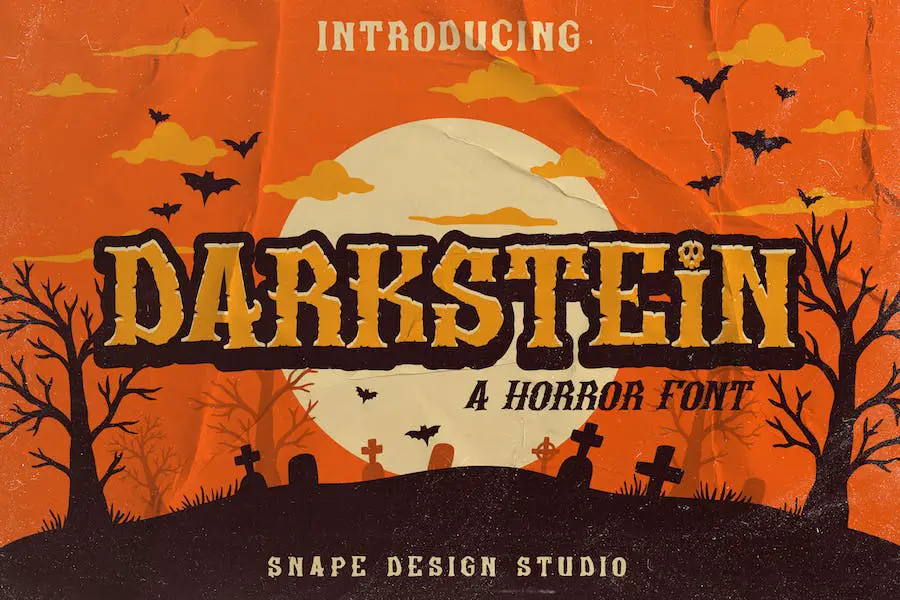
Darkstein เป็นฟอนต์สยองขวัญที่เหมาะเป็นอย่างยิ่งสำหรับการเพิ่มสัมผัสที่น่ากลัวให้กับงานออกแบบของคุณ ไม่ว่าคุณจะกำลังทำโปสเตอร์ปาร์ตี้ฮัลโลวีนหรือสร้างโลโก้ภาพยนตร์ที่น่ากลัว Darkstein จะทำให้โปรเจกต์ของคุณโดดเด่นอย่างแน่นอน
ฟอนต์นี้ดูขี้เล่นแต่น่ากลัว ทำให้ใช้งานได้หลากหลายสำหรับโปรเจ็กต์ต่างๆ เช่น สารคดี ชื่อภาพยนตร์ ปกหนังสือ และอื่นๆ
ให้ Darkstein ปลดปล่อยเสน่ห์ที่น่าขนลุกและนำความรู้สึกหนาวเหน็บมาสู่งานออกแบบของคุณ ไม่ว่าคุณจะสร้างโปรเจ็กต์ฮัลโลวีนที่น่าขนลุกหรือเพียงแค่ต้องการเพิ่มสัมผัสแห่งความมืดให้กับงานของคุณ Darkstein คือตัวเลือกที่สมบูรณ์แบบ
เตรียมพร้อมที่จะทำให้งานออกแบบของคุณโดดเด่นด้วยฟอนต์ชวนขนหัวลุกนี้
ความสุขสยองขวัญ
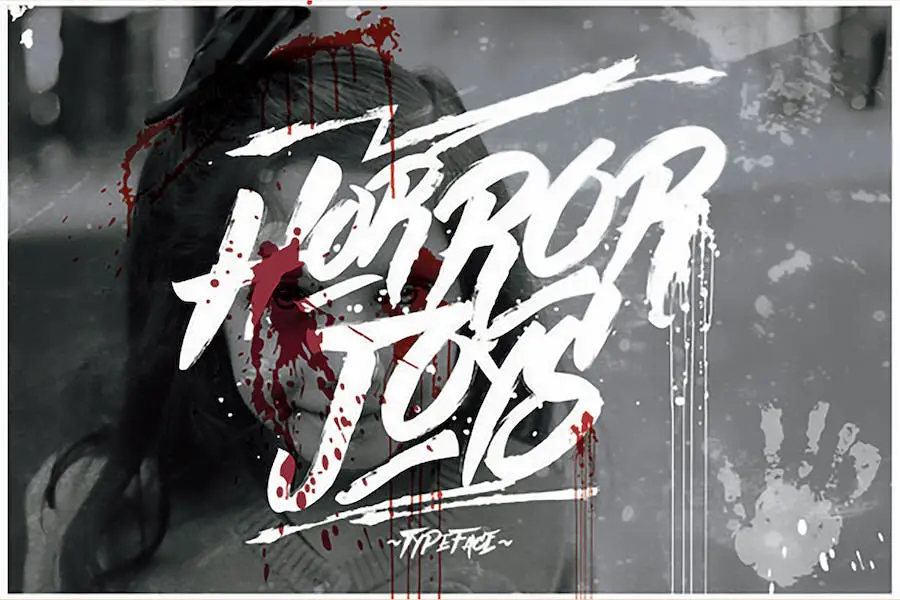
Horror Joys เป็นแบบอักษรสยองขวัญที่ได้รับแรงบันดาลใจจากภาพยนตร์สยองขวัญ มันให้ความรู้สึกแบบแฮนด์เมดที่เพิ่มความน่าขนลุกให้กับงานออกแบบที่เกี่ยวกับหนังสยองขวัญ โปสเตอร์หนัง โปสเตอร์เพลงดังๆ และโปรเจกต์ที่คล้ายกัน
หากคุณชอบความลึกลับ ตำนาน และเรื่องผี ฟอนต์นี้เหมาะสำหรับคุณ เตรียมพร้อมเพิ่มความหลอนให้กับงานออกแบบของคุณด้วย Horror Joys
ด้วยการออกแบบที่ได้รับแรงบันดาลใจจากภาพยนตร์สยองขวัญ Horror Joys นำบรรยากาศที่ไม่เหมือนใครและหนาวเหน็บมาสู่โปรเจ็กต์ของคุณ ความสวยงามแบบแฮนด์เมดทำให้แตกต่างจากฟอนต์อื่นๆ ทำให้งานออกแบบของคุณรู้สึกแตกต่างและน่าขนลุก
ไม่ว่าคุณจะกำลังสร้างโปสเตอร์ภาพยนตร์ หน้าปกเพลย์ลิสต์ชวนสยอง หรืองานออกแบบใดๆ ที่ต้องการสัมผัสที่น่าขนลุก Horror Joys จะยกระดับงานของคุณไปสู่ระดับใหม่ทั้งหมด
ซูซานสไตน์
Suzanstein เป็นแบบอักษรที่ผสมผสานองค์ประกอบสยองขวัญและเรโทรเพื่อสร้างการออกแบบที่หรูหราและซับซ้อนยิ่งขึ้น มันนอกเหนือไปจากธีมผีและเศร้าทั่วไปที่เกี่ยวข้องกับความมืด ช่วยให้คุณสำรวจความเป็นไปได้ที่หลากหลายยิ่งขึ้น
ฟอนต์นี้ไม่จำกัดเฉพาะธีมสยองขวัญเท่านั้น นอกจากนี้ยังสามารถใช้สื่อถึงความมืดมน ความหลงใหล ความอ่อนเยาว์ ความเพ้อฝัน และแม้แต่ประเด็นทางสังคม มีความสามารถรอบด้านและสามารถนำสัมผัสที่ไม่เหมือนใครมาสู่งานออกแบบของคุณได้
Suzanstein เป็นฟอนต์ตัวพิมพ์ใหญ่ทั้งหมดที่มีตัวพิมพ์เล็ก นอกจากนี้ยังมีคุณสมบัติ OpenType ซึ่งเพิ่มความหลากหลายและตัวเลือกที่สร้างสรรค์ให้กับงานออกแบบของคุณ ไม่ว่าคุณจะออกแบบโลโก้ โปสเตอร์ ใบปลิว คำคม ปกหนังสือ หรือบทความสั้นๆ Suzanstein คือตัวเลือกที่ยอดเยี่ยม
ความเศร้าโศก
Sorrow – ฟอนต์สยองขวัญเป็นฟอนต์สำหรับตกแต่งที่นำกลิ่นอายน่ากลัว น่าขนลุก และลึกลับมาสู่โปรเจ็กต์การออกแบบใดๆ เหมาะอย่างยิ่งสำหรับผลิตภัณฑ์ที่จับต้องได้และดิจิทัลที่มีธีมสยองขวัญ น่ากลัว หรือโกธิค แบบอักษรนี้จะทำให้โครงการของคุณมีบรรยากาศที่แตกต่างและเยือกเย็น
ด้วย Sorrow – Horror Font คุณสามารถสร้างงานออกแบบที่น่าดึงดูดซึ่งสร้างความประทับใจไม่รู้ลืม สไตล์ที่เป็นเอกลักษณ์และน่าขนลุกทำให้แตกต่างจากฟอนต์ปกติ จึงเหมาะสำหรับงานฮาโลวีน โปสเตอร์หนังสยองขวัญ ปกหนังสือ และอื่นๆ
ฟอนต์นี้จะเพิ่มสัมผัสแห่งความมืดและความตื่นเต้นให้กับงานออกแบบของคุณ ทำให้โดดเด่น
ฟอนต์ Sorrow นั้นเกี่ยวกับการสร้างประสบการณ์ที่น่าปวดหัว ขอบหยักและรายละเอียดที่คมชัดทำให้เกิดความรู้สึกไม่สบายใจและลึกลับ เมื่อใช้ในงานออกแบบของคุณ ฟอนต์นี้จะทำให้ผู้ชมสั่นสะท้านและดึงดูดความสนใจของพวกเขา
ปีศาจ
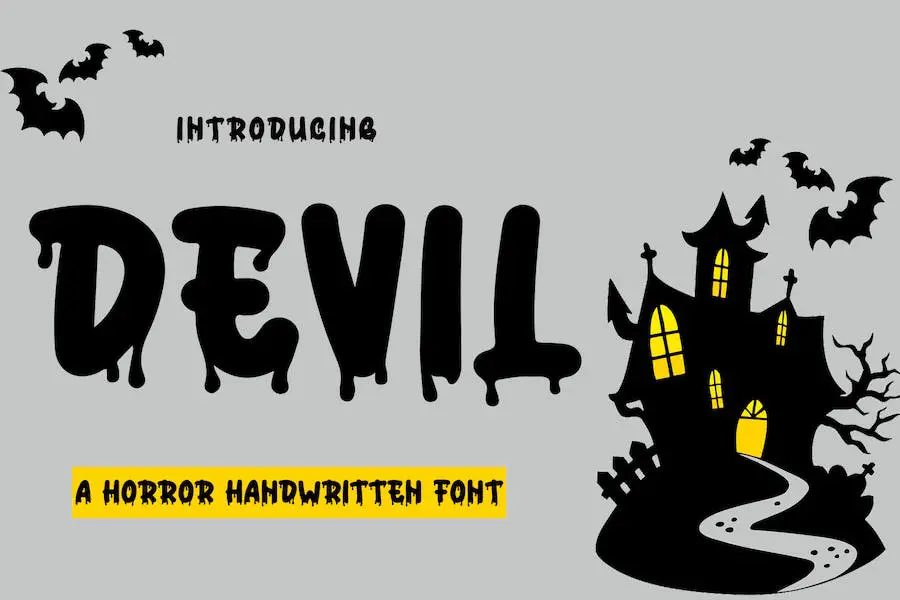
Devil แบบอักษรที่น่ากลัวเหมาะสำหรับการเพิ่มสัมผัสเย็นให้กับโครงการออกแบบกราฟิกของคุณ ลายมือสยองขวัญนี้มาพร้อมกับตัวอักษรสำรองและอักษรควบที่หลากหลาย ช่วยให้คุณสามารถปรับแต่งข้อความของคุณและสร้างแบบอักษรที่แสดงที่ไม่เหมือนใคร
ไม่ว่าคุณจะทำงานในโครงการบรรณาธิการ ออกแบบโลโก้ สร้างแบรนด์เสื้อผ้า บรรจุภัณฑ์ผลิตภัณฑ์ หรือเพิ่มข้อความซ้อนทับที่มีสไตล์ลงในรูปภาพ Devil เป็นตัวเลือกอเนกประสงค์ที่จะปรับปรุงการออกแบบของคุณ
ด้วยความรู้สึกที่ทำด้วยมือและความใส่ใจในรายละเอียด Devil จึงเพิ่มบรรยากาศที่น่าขนลุกให้กับทุกโครงการ ฟีเจอร์ OpenType ของฟอนต์นี้ให้คุณเข้าถึงตัวอักษรสำรองและอักษรควบที่หลากหลาย ช่วยให้คุณสร้างข้อความที่โดดเด่น
ไม่ว่าคุณจะต้องการสร้างส่วนหัวของนิตยสารที่น่ากลัวหรือใส่ความน่ากลัวลงในบรรจุภัณฑ์ผลิตภัณฑ์ของคุณ Devil ช่วยคุณได้
เสียสละ
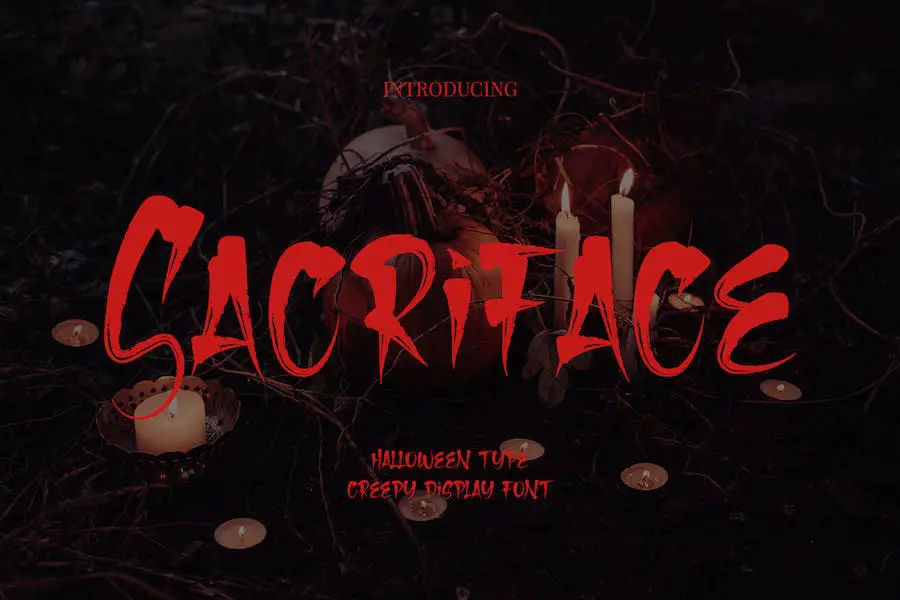
Sacriface เป็นแบบอักษรที่น่ากลัวที่จะเพิ่มความสยองขวัญให้กับงานออกแบบของคุณ ไม่ว่าคุณจะทำงานในโปรเจ็กต์ฮัลโลวีนหรือสร้างโปสเตอร์ภาพยนตร์สำหรับภาพยนตร์สยองขวัญ ฟอนต์นี้เป็นสิ่งที่ต้องมีในคอลเลกชันของคุณ รูปลักษณ์ที่ไม่เหมือนใครและเย็นชารับประกันได้ว่าจะยกระดับการสร้างสรรค์ของคุณไปอีกขั้น
ด้วย Sacriface คุณสามารถดึงเอาบรรยากาศอันน่าขนลุกของงานออกแบบของคุณออกมาได้อย่างง่ายดาย สไตล์ที่น่าขนลุกและหลอนของมันจับใจความสำคัญของทุกสิ่งที่สยองขวัญ ทำให้สมบูรณ์แบบสำหรับโปรเจกต์ใดๆ ก็ตามที่ต้องการทำให้เกิดความรู้สึกหวาดกลัวหรือลุ้นระทึก
ไม่ว่าคุณจะออกแบบบัตรเชิญชวนสยองหรือสร้างโลโก้เท่ๆ ฟอนต์นี้จะเพิ่มปัจจัยที่ทำให้ตกใจเข้าไปอีก
หนึ่งในคุณสมบัติที่โดดเด่นของ Sacriface คือความเก่งกาจ สามารถใช้ในการออกแบบและธีมที่หลากหลาย ทำให้เป็นทรัพย์สินที่มีค่าสำหรับนักออกแบบกราฟิกทุกคน
ไม่ว่าหัวข้อหรือแนวคิดใด ฟอนต์นี้สามารถเปลี่ยนการสร้างสรรค์ธรรมดาๆ ให้เป็นสิ่งที่น่าดึงดูดใจและเสียวสันหลังวาบได้ มันมีพลังในการยกระดับการออกแบบไปสู่อีกระดับอย่างแท้จริง
ลึก
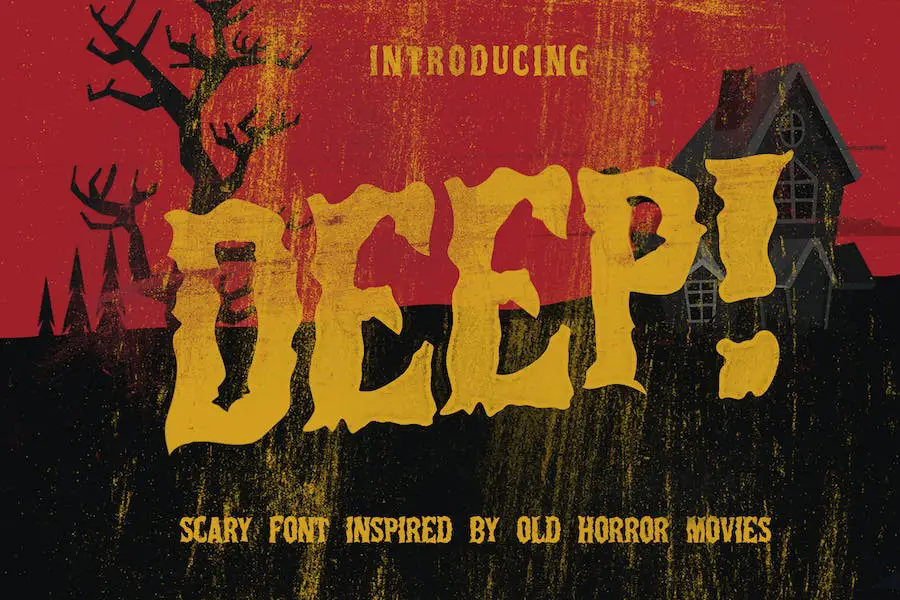
Deep เป็นแบบอักษรที่น่ากลัวซึ่งได้รับแรงบันดาลใจจากภาพยนตร์สยองขวัญเก่าๆ มีทั้งแบบปกติและแบบเอียง ทำให้ใช้งานได้หลากหลายสำหรับโครงการออกแบบต่างๆ
ไม่ว่าคุณจะทำงานเกี่ยวกับการออกแบบองค์ประกอบ คำเชิญงานแต่งงาน การออกแบบเสื้อยืด โลโก้ ป้าย สติ๊กเกอร์ หรืองานสร้างสรรค์อื่นๆ Deep จะเพิ่มความสง่างามที่น่าขนลุกให้กับงานออกแบบของคุณ
ฟอนต์สยองขวัญนี้เหมาะสำหรับการส่งข้อความที่มีเสียงดัง ด้วยรูปลักษณ์ที่โดดเด่นและสะดุดตา Deep สร้างขึ้นด้วยเครื่องหมายแบน นำเสนอการเคลื่อนไหวที่สมจริงในการออกแบบ เพิ่มความสมจริงอีกชั้น
แบบอักษรนี้เหมาะอย่างยิ่งสำหรับโลโก้ ป้ายชื่อ คำพูดที่เขียนด้วยลายมือ บรรจุภัณฑ์ของผลิตภัณฑ์ สินค้า โพสต์บนโซเชียลมีเดีย และแม้แต่การ์ดอวยพร นอกจากนี้ยังใช้งานได้อย่างมหัศจรรย์กับการออกแบบเสื้อยืดและผลิตภัณฑ์เสื้อผ้าอื่นๆ ช่วยให้คุณสร้างเครื่องแต่งกายที่น่าสนใจและเสียวสันหลังวาบ
ฟอนต์แสดงสยองขวัญ Gendaruwo
Gendaruwo – Horror Display Font เป็นฟอนต์ที่น่ากลัวจนน่าตกใจซึ่งเหมาะอย่างยิ่งสำหรับการเพิ่มสัมผัสที่เสียวสันหลังให้กับงานออกแบบและโปรเจ็กต์ฮัลโลวีนของคุณ
ไม่ว่าคุณจะสร้างใบปลิวชวนสยอง ชื่อภาพยนตร์ที่น่าขนลุก หรือปกหนังสือที่น่าสะพรึงกลัว ฟอนต์นี้จะทำให้คำนี้มีชีวิตขึ้นมาด้วยลูกเล่นที่น่าสะพรึงกลัว
ด้วยรายละเอียดที่เต็มไปด้วยเลือดและความสวยงามที่น่าขนลุก GENDARUWO จึงเป็นตัวเลือกที่ดีที่สุดสำหรับผู้ที่ต้องการปลุกความรู้สึกหวาดกลัวและสยองขวัญ รูปแบบตัวอักษรที่บิดเบี้ยวและบิดเบี้ยวจะทำให้งานออกแบบของคุณดูน่ากลัว ทำให้มั่นใจได้ว่าจะโดดเด่นและดึงดูดความสนใจ
แบบอักษรที่น่ากลัวนี้ไม่ได้จำกัดเฉพาะงานฮาโลวีนเท่านั้น นอกจากนี้ยังสามารถใช้สำหรับสร้างการ์ตูนน่าขนลุก โปสเตอร์ที่สะดุดตา แบนเนอร์สุดหลอน สินค้าที่ไม่ซ้ำใคร และอื่นๆ อีกมากมาย ความเป็นไปได้ไม่มีที่สิ้นสุดเมื่อพูดถึงการปลดปล่อยความน่ากลัวของ GENDARUWO
เมทัลมอล
Metalmol เป็นฟอนต์ Horror Metal ที่แตกต่าง มีรายละเอียดสูง ซึ่งเหมาะสำหรับนักออกแบบกราฟิกที่ต้องการค้นหาฟอนต์เพื่อปรับปรุงการออกแบบโครงการของพวกเขา
ด้วยคุณสมบัติที่เป็นเอกลักษณ์ Metalmol จึงเป็นตัวเลือกที่ยอดเยี่ยมสำหรับการใช้งานที่หลากหลาย รวมถึงการออกแบบย้อนยุคในเมือง การสร้างแบรนด์ธุรกิจรอยสัก โลโก้ การออกแบบวินเทจ และอื่นๆ
เมื่อพูดถึงแบบอักษรที่น่ากลัว Metalmol เป็นตัวเลือกที่ยอดเยี่ยม การออกแบบที่สลับซับซ้อนทำให้มีกลิ่นอายเหมือนผีและน่าขนลุก จึงเหมาะสำหรับโปรเจกต์ธีมฮัลโลวีนหรืองานออกแบบที่ต้องการกระตุ้นความรู้สึกสยองขวัญ
ไม่ว่าคุณกำลังทำงานกับโปสเตอร์ เว็บไซต์ หรือใบปลิว Metalmol สามารถนำสัมผัสแห่งความมืดและความน่ากลัวมาสู่งานออกแบบของคุณได้อย่างสมบูรณ์แบบ
Cinema Macabre
Cinema Macabre เป็นฟอนต์พู่กันหลวมและหมึกดำที่ได้แรงบันดาลใจจากโปสเตอร์ภาพยนตร์ Giallo สุดคลาสสิก หากคุณเป็นแฟนตัวยงของภาพที่มีสไตล์ เพลงประกอบชวนหลอน และการตลาดที่นำไปสู่การแสวงหาผลประโยชน์ของภาพยนตร์สยองขวัญในช่วงปี 1960 ถึง 1980 ฟอนต์นี้จะต้องจับความรู้สึกสยองขวัญแบบวินเทจได้อย่างแน่นอน
Cinema Macabre ได้รับการออกแบบมาเพื่อรักษารายละเอียดแบบอะนาล็อกของงานพิมพ์เก่า มีความหลากหลายเพียงพอที่จะทำงานในการออกแบบดิจิทัลต่างๆ
ตระกูลฟอนต์ It ประกอบด้วยฟอนต์ที่ไม่ซ้ำกันหกฟอนต์ แต่ละฟอนต์มีชุดอักขระตัวพิมพ์ใหญ่และตัวพิมพ์เล็ก ตัวเลข เครื่องหมายวรรคตอน และการสนับสนุนภาษาของตัวเอง แต่นั่นไม่ใช่ทั้งหมด ฟอนต์นี้ไปไกลกว่านั้นด้วยการเสนอตัวอักษรควบ ขีดเส้นใต้ และองค์ประกอบกราฟิกแบบกำหนดเอง
ด้วยคุณสมบัติทั้งหมดเหล่านี้ คุณจะมีกล่องเครื่องมือที่จำเป็นสำหรับการสร้างงานออกแบบชื่อเรื่องที่ทำด้วยมืออย่างแท้จริง
ครีพโชว์
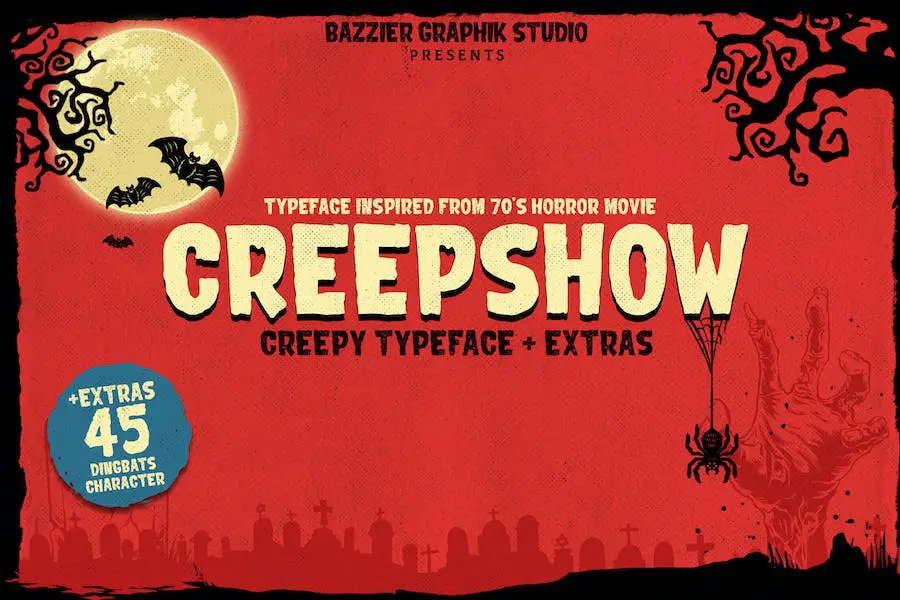
Creepshow เป็นฟอนต์ที่ต้องมีสำหรับนักออกแบบกราฟิกที่ต้องการเพิ่มความน่ากลัวและความน่าขนลุกให้กับโปรเจ็กต์ของพวกเขา เหมาะอย่างยิ่งสำหรับการสร้างโปสเตอร์และการออกแบบภาพยนตร์สยองขวัญคลาสสิกที่ทำให้ผู้ชมของคุณสั่นสะท้านด้วยความกลัว
แบบอักษรนี้มีสองเวอร์ชัน: สะอาดและหยาบ รุ่นสะอาดเรียบและทันสมัย ในขณะที่รุ่นหยาบจะเพิ่มความรู้สึกแบบวินเทจให้กับงานออกแบบของคุณ คุณยังได้รับโบนัสสำหรับเวอร์ชั่นดิงแบท ซึ่งรวมถึงไอคอนและสัญลักษณ์ที่น่าขนลุกเพื่อยกระดับการสร้างสรรค์ที่น่ากลัวของคุณ
ไม่ว่าคุณจะทำงานในโปรเจ็กต์ธีมฮัลโลวีนหรือต้องการเพิ่มองค์ประกอบที่น่ากลัวให้กับงานออกแบบของคุณ Creepshow ช่วยคุณได้ กลิ่นอายที่น่าขนลุกและเยือกเย็นของมันจะดึงดูดความสนใจของผู้ชมและทำให้พวกเขารู้สึกไม่สบายใจ
แจ็คแม็กซ์
Jacmax เป็นแบบอักษรที่แสดงซึ่งนำความรู้สึกเย็นชาและน่าขนลุกมาสู่งานออกแบบของคุณ ด้วยสไตล์สยองขวัญที่เป็นเอกลักษณ์และการตกแต่ง มันจึงเป็นตัวเลือกที่สมบูรณ์แบบสำหรับโปรเจกต์แนวสยองขวัญ
ไม่ว่าคุณจะกำลังสร้างโปสเตอร์ภาพยนตร์ ออกแบบตัวอักษรสำหรับปกหนังสือ สร้างปกอัลบั้ม หรือพัฒนาโลโก้ที่น่ากลัว Jacmax ช่วยคุณได้
แบบอักษรนี้ออกแบบมาเพื่อเพิ่มความสยองขวัญให้กับโปรเจ็กต์ของคุณโดยเฉพาะ ทำให้เหมาะสำหรับการออกแบบวงจร การสร้าง Figma และแม้แต่การออกแบบรอยสัก ลองนึกภาพผลกระทบของการใช้ฟอนต์นี้สำหรับโปรเจ็กต์ธีมฮัลโลวีนหรือสร้างรอยสักที่บิดเบี้ยวเหมือนผี
ด้วย Jacmax คุณสามารถยกระดับการออกแบบของคุณไปอีกขั้นและสร้างบรรยากาศที่น่ากลัวอย่างแท้จริง
แฮนด์โลว์
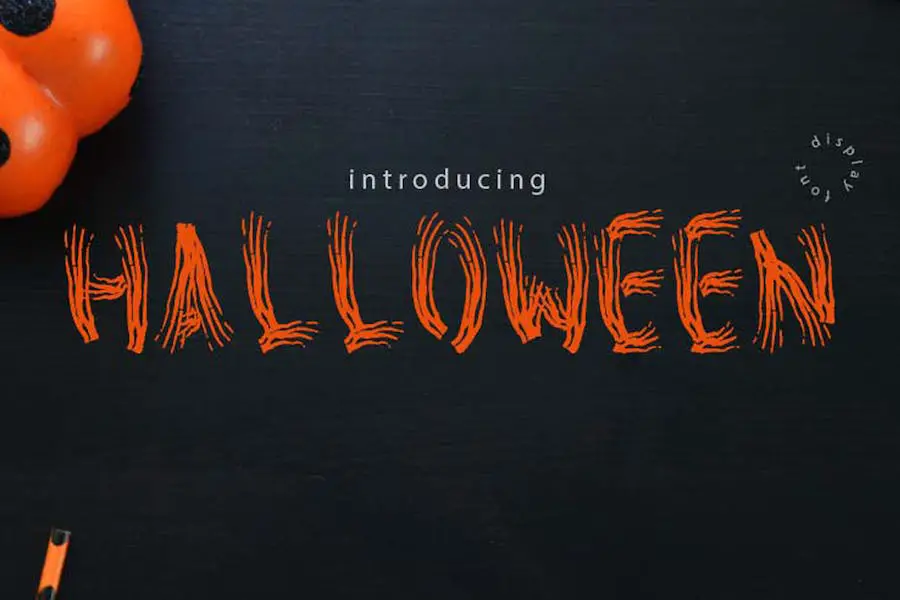
handloween เป็นแบบอักษรฮัลโลวีนชวนสยองที่ได้รับแรงบันดาลใจจากความแตกต่างแบบโกธิก น่ากลัว การประท้วง และสยองขวัญ ด้วยการออกแบบที่เป็นเอกลักษณ์และความสวยงามที่น่าขนลุก มันจึงเป็นตัวเลือกที่สมบูรณ์แบบสำหรับนักออกแบบกราฟิกที่ต้องการเพิ่มความน่ากลัวให้กับโครงการของพวกเขา
แบบอักษรสยองขวัญนี้เป็นเครื่องมือในอุดมคติสำหรับการปรับปรุงการออกแบบของโปรเจ็กต์ธีมฮัลโลวีน ไม่ว่าคุณกำลังทำงานเกี่ยวกับการ์ดเชิญ โปสเตอร์ หรือกราฟิกโซเชียลมีเดีย Handloween จะเพิ่มบรรยากาศสบายๆ ให้กับงานสร้างสรรค์ของคุณ
สไตล์โกธิคของฟอนต์ให้ความรู้สึกลึกลับและน่ากลัว ในขณะที่องค์ประกอบที่น่ากลัวทำให้มันโดดเด่นกว่าฟอนต์ดั้งเดิม เป็นฟอนต์ที่สื่อถึงวิญญาณสยองขวัญของวันฮัลโลวีนและจะต้องดึงดูดใจผู้ชมอย่างแน่นอน
ซอมบี้กำลังมา
Zombie Coming เป็นแบบอักษรฮัลโลวีนที่น่ากลัวซึ่งเพิ่มความน่าขนลุกให้กับโครงการออกแบบของคุณ ฟอนต์สำหรับแสดงผลนี้มีลักษณะกราฟฟิตีแบบลายเส้นหยดเดียว ทำให้สมบูรณ์แบบสำหรับการสร้างแบรนด์ หัวเรื่อง โลโก้ ฉลาก และอื่นๆ ที่น่าขนลุก
ด้วยตัวเลือกการสลับ คุณสามารถยกระดับการออกแบบของคุณไปอีกขั้นและสร้างรูปลักษณ์ที่ไม่เหมือนใคร ไม่ว่าคุณจะทำงานในโปรเจ็กต์ธีมฮัลโลวีนหรือแค่ต้องการเพิ่มความรู้สึกน่าขนลุกให้กับงานออกแบบของคุณ Zombie Coming คือตัวเลือกที่สมบูรณ์แบบ
เพิ่มความน่ากลัวให้กับงานออกแบบของคุณด้วยฟอนต์ชวนสยองนี้
บาราคูด้ามอนสเตอร์
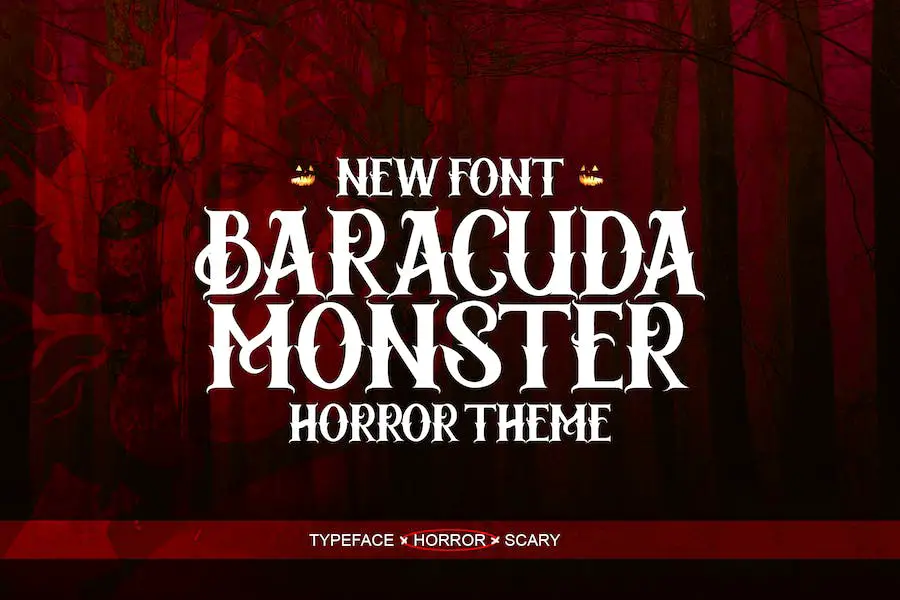
Baracuda Monster เป็นฟอนต์สยองขวัญอเนกประสงค์ที่สมบูรณ์แบบสำหรับเพิ่มสัมผัสที่น่ากลัวให้กับงานออกแบบของคุณ ไม่ว่าคุณจะทำงานในโปรเจ็กต์ธีมฮัลโลวีนหรือสร้างงานออกแบบโกธิค ฟอนต์นี้จะสร้างความตื่นตระหนกได้อย่างเหมาะสม
เหมาะอย่างยิ่งสำหรับภาพยนตร์สยองขวัญและโปรเจ็กต์ที่ต้องการบรรยากาศน่ากลัวและน่าขนลุก
ด้วย Baracuda Monster คุณจะสามารถเข้าถึงแบบอักษรที่รวบรวมแก่นแท้ของวันฮาโลวีนและแนวสยองขวัญ ความสวยงามที่เยือกเย็นและน่าขนลุกจะทำให้งานออกแบบของคุณโดดเด่นเป็นพิเศษ ทำให้พวกเขาโดดเด่นกว่าใคร
ใช้สำหรับโปสเตอร์ ใบปลิว กราฟิกเว็บไซต์ หรือโครงการใดๆ ที่คุณต้องการทำให้เกิดความรู้สึกหวาดกลัวและความลึกลับ
รายละเอียดที่ซับซ้อนและรูปแบบตัวอักษรที่ไม่เหมือนใครของฟอนต์นี้ทำให้นักออกแบบกราฟิกทุกคนที่ต้องการพัฒนาเกมสยองขวัญต้องมี การออกแบบที่สร้างขึ้นมาอย่างพิถีพิถันทำให้มั่นใจได้ว่ายังคงอ่านได้ในขณะที่ยังคงสไตล์ที่แตกต่าง
ขอบที่แหลมคมและส่วนโค้งที่น่าดึงดูดใจของตัวอักษรแต่ละตัวจะทำให้คุณรู้สึกเสียวสันหลังวาบ
มัสคิล
Mustkill เป็นแบบอักษรฮัลโลวีนที่น่ากลัวซึ่งได้รับแรงบันดาลใจจากโปสเตอร์ภาพยนตร์สยองขวัญ ด้วยรายละเอียดที่หยาบและรูปแบบตัวพิมพ์ใหญ่ ฟอนต์นี้แสดงอารมณ์โกรธและฝันร้าย
ไม่ว่าคุณจะกำลังทำโปสเตอร์ โครงการสร้างแบรนด์ โลโก้ ปกหนังสือ หรืองานโปรโมตฮาโลวีน Mustkill คือตัวเลือกที่สมบูรณ์แบบที่จะนำสัมผัสที่น่าขนลุกและน่ากลัวมาสู่งานออกแบบของคุณ
หนึ่งในคุณสมบัติที่โดดเด่นของ Mustkill คือการรองรับหลายภาษา โดยครอบคลุมภาษาละตินมากกว่า 60 ภาษา ซึ่งหมายความว่าไม่ว่าผู้ชมของคุณจะมาจากที่ใด คุณก็สามารถสื่อสารความสยองขวัญและความน่ากลัวในภาษาของพวกเขาได้อย่างมีประสิทธิภาพ
ฟอนต์ยังมีตัวสลับและตัวควบ ให้คุณทดลองและสร้างชุดตัวอักษรที่ไม่เหมือนใครซึ่งช่วยเพิ่มเอฟเฟ็กต์ที่น่าสะพรึงกลัว เพิ่มลูกเล่นและเอกลักษณ์ให้กับงานออกแบบของคุณด้วยตัวเลือกเพิ่มเติมเหล่านี้
เครื่องเคมี
คุณกำลังค้นหาแบบอักษรที่สมบูรณ์แบบเพื่อเพิ่มความน่ากลัวและน่าขนลุกให้กับโครงการออกแบบกราฟิกของคุณหรือไม่? ไม่ต้องมองหาที่ไหนอีกแล้ว เพราะ Chemical Machines พร้อมตอบสนองทุกความต้องการของคุณ
แบบอักษรนี้เป็นตัวอย่างที่ดีเลิศของความสยองขวัญและสไตล์เรโทร ออกแบบมาเพื่อให้งานออกแบบของคุณมีบรรยากาศที่เยือกเย็นอย่างแท้จริง ด้วย Chemical Machines ไม่มีขีดจำกัดในการสร้างสรรค์ของคุณ
ไม่ว่าคุณจะกำลังทำงานกับภาพประกอบสีเดียวหรือทดลองเอฟเฟกต์ข้อความไล่ระดับสีสมัยใหม่ ฟอนต์นี้จะเพิ่มความน่ากลัวให้กับคุณ
แต่นั่นไม่ใช่ทั้งหมด เครื่องจักรเคมียังช่วยให้คุณใส่การออกแบบของคุณด้วยศิลปะเหนือจริงและป๊อปอาร์ต ปลดปล่อยจินตนาการของคุณและปล่อยให้ความคิดสร้างสรรค์ของคุณโลดแล่น!
ผี
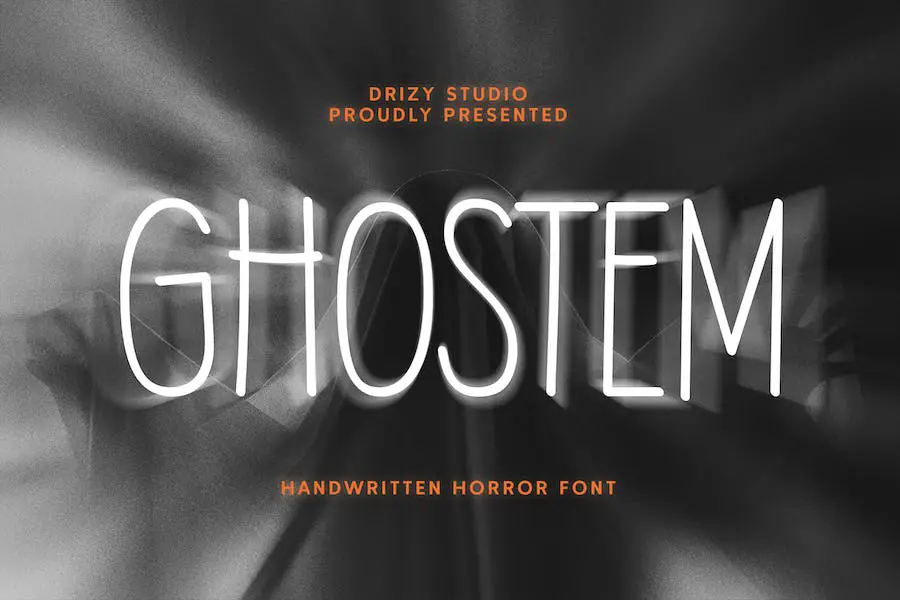
Ghostem เป็นฟอนต์สยองขวัญที่เขียนด้วยลายมือที่ยอดเยี่ยมจากสตูดิโอ Drizy ซึ่งเหมาะสำหรับการสร้างบรรยากาศที่น่ากลัวและน่ากลัวในโครงการออกแบบของคุณ โดยเฉพาะอย่างยิ่งสำหรับวันฮัลโลวีน
ฟอนต์นี้มีรูปแบบที่จำเป็นทั้งหมดที่คุณต้องการ รวมทั้งตัวพิมพ์ใหญ่และตัวพิมพ์เล็กสลับกัน ตัวเลข เครื่องหมายวรรคตอน และการสนับสนุนหลายภาษา
ด้วย Ghostem คุณสามารถเพิ่มสัมผัสที่เยือกเย็นให้กับงานออกแบบของคุณและทำให้ผู้ชมดื่มด่ำไปกับโลกแห่งสยองขวัญได้อย่างง่ายดาย ไม่ว่าคุณจะทำงานเกี่ยวกับโปสเตอร์ บัตรเชิญ หรือกราฟิกเว็บไซต์ ฟอนต์นี้ช่วยคุณได้ เตรียมตัวให้พร้อมสำหรับการออกแบบที่เสียวสันหลังด้วย Ghostem!
ชั่วร้าย
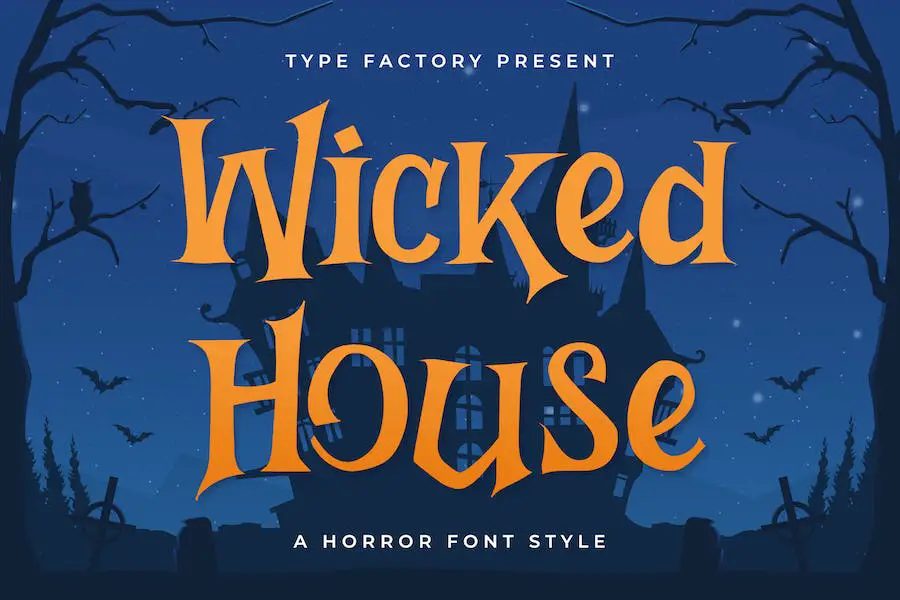
Wicked เป็นฟอนต์สยองขวัญที่น่าอัศจรรย์และน่าขนลุกที่จะนำความรู้สึกเยือกเย็นและน่าหลงใหลมาสู่โปรเจกต์การออกแบบของคุณ
แบบอักษรนี้เหมาะสำหรับการสร้างบรรยากาศที่น่าขนลุกในเกมแฟนตาซี หนังสือนิทานสยองขวัญสำหรับเด็ก โลโก้ การสร้างแบรนด์ การโฆษณา โปรเจกต์ฮัลโลวีน การออกแบบโกธิค เครื่องแต่งกาย รอยสัก และอื่นๆ!
ด้วยสัญลักษณ์และเครื่องหมายวรรคตอนที่เป็นเอกลักษณ์ Wicked ช่วยให้คุณเพิ่มความน่าขนลุกให้กับงานออกแบบของคุณได้ ฟอนต์ยังให้การสนับสนุนหลายภาษา เพื่อให้แน่ใจว่าคุณสามารถใช้ในภาษาต่างๆ ได้โดยไม่มีปัญหาใดๆ
Wicked โดดเด่นด้วยตัวอักษรทั้งตัวพิมพ์ใหญ่และตัวพิมพ์เล็ก ทำให้คุณมีความยืดหยุ่นในการสร้างตัวพิมพ์ที่สะดุดตา นอกจากนี้ยังมีตัวเลข ทำให้คุณสามารถแสดงตัวเลขในรูปแบบที่เสียวสันหลังวาบ
บีสต์แมน
Beastman เป็นแบบอักษรที่น่ากลัวซึ่งเหมาะสำหรับโครงการออกแบบต่างๆ ไม่ว่าคุณกำลังสร้างโลโก้ วัสดุสำหรับสร้างแบรนด์ หรือโฆษณา ฟอนต์นี้จะเพิ่มความน่าขนลุกและไม่เหมือนใคร
นอกจากนี้ยังเหมาะสำหรับหนังสือเด็ก การ์ตูน และแอนิเมชันอีกด้วย ด้วย Beastman คุณสามารถสร้างโปสเตอร์ที่สะดุดตา ปกหนังสือ และการออกแบบบรรณาธิการได้อย่างง่ายดาย
ใช้งานได้อเนกประสงค์บนเว็บไซต์และบล็อก ตลอดจนบนการ์ด แก้วน้ำ และเสื้อยืด ไม่ว่าความต้องการด้านการเขียนด้วยลายมือของคุณจะเป็นอย่างไร Beastman ช่วยคุณได้
Snarky ลูกสุนัข
Snarky Puppy เป็นแบบอักษรที่น่ากลัวและน่าขนลุกซึ่งเหมาะสำหรับการเพิ่มความสยองขวัญให้กับโครงการออกแบบของคุณ ไม่ว่าคุณกำลังทำงานเกี่ยวกับการออกแบบโลโก้ หัวจดหมาย โปสเตอร์ หรือเครื่องแต่งกาย ฟอนต์นี้จะทำให้โดดเด่นได้อย่างแน่นอน
ด้วย Snarky Puppy คุณจะได้รับคุณสมบัติมากมายที่จะปรับปรุงการออกแบบของคุณ มันรวมถึงทางเลือกอื่น ลิเกเจอร์ และลิเกเจอร์มาตรฐาน ให้คุณมีตัวเลือกมากมายให้เลือก การติดตั้งทำได้ง่ายและไม่ยุ่งยาก ทำให้ทุกคนสามารถเข้าถึงได้
คุณไม่ต้องกังวลเกี่ยวกับความเข้ากันได้เช่นกัน Snarky Puppy ทำงานได้อย่างราบรื่นกับซอฟต์แวร์การออกแบบยอดนิยม เช่น Adobe Illustrator, Adobe Photoshop, Adobe InDesign และแม้แต่ Microsoft Word นอกจากนี้ยังรองรับหลายภาษา ทำให้มีความหลากหลายสำหรับทุกโครงการ
ตอบโต้
Counter Attack เป็นฟอนต์สยองขวัญที่เพิ่มความน่ากลัวให้กับโปรเจกต์การออกแบบ แบบอักษรนี้ได้รับแรงบันดาลใจจากแนวสยองขวัญ เหมาะอย่างยิ่งสำหรับการถ่ายภาพแนวสยองขวัญและน่าขนลุก
ไม่ว่าคุณจะทำงานเกี่ยวกับโลโก้ โปสเตอร์ ปกหนังสือ หรือแม้แต่การออกแบบเสื้อยืด Counter Attack จะสร้างความประทับใจให้คุณอย่างแน่นอน
ฟอนต์ที่แสดงนี้มีทั้งตัวพิมพ์ใหญ่และตัวพิมพ์เล็ก ทำให้การออกแบบของคุณมีความหลากหลาย นอกจากนี้ยังมีการสนับสนุนหลายภาษา คุณจึงสามารถใช้ในโครงการในภาษาต่างๆ ได้
ด้วยตัวเลข สัญลักษณ์ และเครื่องหมายวรรคตอน Counter Attack มีทุกสิ่งที่คุณต้องการเพื่อสร้างองค์ประกอบที่เยือกเย็น
เดดไนท์
Dead Night เป็นฟอนต์แนวสยองขวัญที่สมบูรณ์แบบสำหรับนักออกแบบกราฟิกที่ต้องการเพิ่มความน่าขนลุกให้กับโปรเจ็กต์ของพวกเขา ด้วยสไตล์การประดิษฐ์ตัวอักษร ฟอนต์นี้จึงเหมาะอย่างยิ่งสำหรับการสร้างคำเชิญที่สวยงาม การ์ดอวยพร วัสดุสำหรับสร้างแบรนด์ นามบัตร คำพูด โปสเตอร์ และอื่นๆ
มันมีตัวอักษรและตัวอักษรสลับกันทำให้การออกแบบของคุณมีเอกลักษณ์และสะดุดตายิ่งขึ้น
การติดตั้ง Dead Night ทำได้ง่ายและไม่ยุ่งยาก เนื่องจากสามารถเข้าถึงได้ใน Adobe Illustrator, Adobe Photoshop, Adobe InDesign และแม้แต่ Microsoft Word คุณไม่จำเป็นต้องมีซอฟต์แวร์การออกแบบเพิ่มเติมเพื่อเข้าถึงอักขระที่เข้ารหัส PUA ได้อย่างเต็มที่
ฟอนต์ยังรวมคุณสมบัติ Open Type ต่างๆ เช่น ชุดโวหาร การสลับตามบริบท การสวอช และลิเกเจอร์ คุณลักษณะเหล่านี้สามารถใช้งานได้ง่ายในโปรแกรมต่างๆ เช่น Adobe Illustrator, Adobe InDesign, Adobe Photoshop, Corel Draw X version และ Microsoft Word
แบบอักษรสยองขวัญฟรีที่ดีที่สุด
ต้องการเพิ่มความน่ากลัวให้กับโครงการออกแบบของคุณหรือไม่? มองไม่เพิ่มเติม! รายการฟอนต์สยองขวัญฟรีที่ดีที่สุดที่เราคัดสรรมานั้นจะทำให้งานออกแบบของคุณดูน่าดึงดูดใจอย่างแน่นอน ดำดิ่งและสำรวจเสน่ห์ที่น่าขนลุกของฟอนต์เหล่านี้ – คุณจะไม่สามารถต้านทานได้!
สยองขวัญ
Horror เป็นฟอนต์ที่น่าดึงดูดใจที่สร้างขึ้นโดย Ni Luh Purnamawati ซึ่งเหมาะอย่างยิ่งสำหรับการเพิ่มกลิ่นอายที่น่ากลัวและน่าขนลุกให้กับโปรเจกต์การออกแบบของคุณ ฟอนต์นี้สามารถใช้ได้ฟรีสำหรับการใช้งานส่วนตัว ทำให้น่าดึงดูดยิ่งขึ้น
ด้วย Horror คุณสามารถสร้างการออกแบบที่สะดุดตาและน่าขนลุกที่จะสร้างความประทับใจไม่รู้ลืม รูปแบบตัวอักษรที่บิดเบี้ยวเป็นเอกลักษณ์ให้ความรู้สึกเยือกเย็นและฝันร้ายกับทุกข้อความ
ไม่ว่าคุณจะทำงานกับกราฟิกธีมฮัลโลวีน โปสเตอร์หนังสยองขวัญ หรือเพียงต้องการเพิ่มความดาร์กให้กับโปรเจ็กต์ของคุณ ฟอนต์นี้ช่วยคุณได้
คุณลักษณะที่โดดเด่นอย่างหนึ่งของหนังสยองขวัญคือความสามารถในการทำให้เกิดความกลัวและความลึกลับ ขอบหยักและเส้นหนาทำให้ตัวอักษรแต่ละตัวดูเหมือนถูกแกะสลักออกมาจากป่าผีสิง
สยองขวัญ
Horroroid โดย Iconian Fonts เป็นสิ่งที่ต้องมีสำหรับนักออกแบบกราฟิกที่ค้นหาฟอนต์ที่สมบูรณ์แบบเพื่อปรับปรุงการออกแบบโปรเจ็กต์ของพวกเขา คอลเลกชั่นฟอนต์นี้มีฟอนต์ที่น่ากลัวและน่าขนลุกมากมายที่จะเพิ่มความเยือกเย็นให้กับงานออกแบบใดๆ
ด้วย Horroroid คุณสามารถทำให้โปรเจกต์แนวสยองขวัญของคุณมีชีวิตขึ้นมาได้ด้วยการพิมพ์ที่ชวนหลอนและบรรยากาศของมัน
ฟอนต์แต่ละตัวในคอลเลกชั่น Horroroid มีลักษณะและสไตล์ที่เป็นเอกลักษณ์ของตัวเอง ตั้งแต่ฟอนต์สคริปต์ที่เขียนด้วยลายมืออันน่าขนลุกไปจนถึงฟอนต์ที่แสดงตัวหนาและน่ากลัว คอลเลกชันนี้มีครบทุกอย่าง
ไม่ว่าคุณจะสร้างโปสเตอร์ธีมฮัลโลวีน โปสเตอร์หนังสยองขวัญ หรือเว็บไซต์ที่มืดมนและลึกลับ Horroroid มีฟอนต์ที่สมบูรณ์แบบเพื่อถ่ายทอดบรรยากาศที่เหมาะสม
สยองขวัญ
Horrorshow เป็นฟอนต์สยองขวัญที่สร้างโดย Hawtpixel ซึ่งเหมาะอย่างยิ่งสำหรับการเพิ่มสัมผัสที่น่าขนลุกให้กับโปรเจ็กต์การออกแบบกราฟิกของคุณ ออกแบบมาโดยเฉพาะสำหรับการใช้งานส่วนตัว ฟอนต์นี้เป็นสิ่งที่ต้องมีสำหรับนักออกแบบกราฟิกที่ต้องการปรับปรุงโปรเจกต์ด้วยความสวยงามชวนหลอน
ด้วยการออกแบบที่ไม่เหมือนใครและน่าขนลุก Horrorshow จะสร้างความประทับใจให้กับผู้ชมของคุณอย่างแน่นอน
แบบอักษรสยองขวัญนี้มีคุณสมบัติที่น่าประทับใจมากมายซึ่งทำให้โดดเด่นกว่าแบบอักษรอื่น รูปแบบตัวอักษรที่สร้างขึ้นอย่างประณีตให้ความรู้สึกน่าขนลุก สร้างบรรยากาศที่ลุ้นระทึกและน่าติดตาม
มุมที่แหลมคมและรูปทรงที่บิดเบี้ยวช่วยเพิ่มสัมผัสแห่งความมืดให้กับงานออกแบบ ทำให้เหมาะสำหรับโปรเจ็กต์แนวสยองขวัญที่คุณต้องการกระตุ้นความรู้สึกหวาดกลัวและความไม่สบายใจ
สยองขวัญ 666
Horror 666 เป็นฟอนต์ที่ยอดเยี่ยมที่จะทำให้งานออกแบบของคุณมีสัมผัสที่เยือกเย็นและน่าขนลุก ด้วยความสวยงามที่ชวนขนลุก ฟอนต์นี้จึงเหมาะอย่างยิ่งสำหรับการเพิ่มความตื่นเต้นให้กับงานออกแบบของคุณ ออกแบบโดย ManekaDesign และใช้งานส่วนตัวได้ฟรี!
หนึ่งในคุณสมบัติที่สำคัญของ Horror 666 คือสไตล์ที่เป็นเอกลักษณ์และโดดเด่น แบบอักษรมีขอบที่คมและเป็นรอยหยัก ทำให้ดูน่ากลัวอย่างแท้จริง ไม่ว่าคุณจะกำลังสร้างโปสเตอร์ธีมฮัลโลวีน โปสเตอร์หนังสยองขวัญ หรือบัตรเชิญที่น่ากลัว ฟอนต์นี้จะสร้างผลกระทบอย่างแน่นอน
อีกแง่มุมที่ยอดเยี่ยมของ Horror 666 คือความเก่งกาจ ใช้ได้กับทั้งพาดหัวข่าวและเนื้อความ ทำให้คุณสามารถสร้างงานออกแบบที่เหนียวแน่นและดึงดูดใจ
ฟอนต์มีทั้งแบบตัวพิมพ์ใหญ่และตัวพิมพ์เล็ก รวมถึงตัวเลขและเครื่องหมายวรรคตอน ให้คุณมีตัวเลือกมากมายในการเล่น
พื้นที่สยองขวัญ
Horror Area เป็นฟอนต์ฟรีที่สร้างโดย Bangkit Tri Setiadi ซึ่งเหมาะอย่างยิ่งสำหรับการเพิ่มสัมผัสที่น่ากลัวและน่าขนลุกให้กับโปรเจกต์การออกแบบของคุณ แบบอักษรนี้เหมาะสำหรับนักออกแบบกราฟิกที่ต้องการเพิ่มความสวยงามและบรรยากาศโดยรวมของงาน
ด้วย Horror Area คุณสามารถสร้างบรรยากาศที่น่าขนลุกและน่าขนลุกที่จะดึงดูดผู้ชมของคุณได้อย่างง่ายดาย
ด้วยการออกแบบที่ไม่เหมือนใครและชวนหลอน Horror Area เป็นตัวเลือกที่สมบูรณ์แบบสำหรับโครงการที่ต้องการสัมผัสแห่งความมืดและความลึกลับ
ไม่ว่าคุณจะทำงานออกแบบในธีมฮัลโลวีน โปสเตอร์หนังสยองขวัญ หรือปกหนังสือที่น่าสยดสยอง แบบอักษรนี้จะช่วยสร้างความโดดเด่นและสร้างความประทับใจไม่รู้ลืม
คุณลักษณะที่โดดเด่นอย่างหนึ่งของ Horror Area คือความสามารถรอบด้าน สามารถปรับและปรับแต่งได้ง่ายเพื่อให้เหมาะกับความต้องการด้านการออกแบบต่างๆ ด้วยน้ำหนักและสไตล์ที่แตกต่างกัน คุณจึงมีความยืดหยุ่นในการเล่นและทดลองกับรูปลักษณ์ต่างๆ
สเปรย์สยองขวัญ
Horror Spray เป็นฟอนต์สุดวิเศษที่สร้างโดย Elbanadha Creative เหมาะอย่างยิ่งสำหรับนักออกแบบกราฟิกที่ต้องการเพิ่มสัมผัสที่น่ากลัวและน่าขนลุกให้กับโครงการของตน แบบอักษรนี้มีให้ใช้งานส่วนตัวฟรี
เมื่อต้องเลือกฟอนต์ที่เหมาะกับโปรเจ็กต์การออกแบบของคุณ Horror Spray ควรอยู่ในเรดาร์ของคุณอย่างแน่นอน ด้วยบรรยากาศอันน่าขนลุกและเยือกเย็น มันสามารถเปลี่ยนผลงานสร้างสรรค์ของคุณให้กลายเป็นสิ่งที่สวยงามชวนหลอนได้ในทันที
ไม่ว่าคุณจะกำลังทำงานกับโปสเตอร์ เว็บไซต์ หรือโปรเจ็กต์ธีมฮัลโลวีน ฟอนต์นี้จะทำให้งานออกแบบของคุณมีชีวิต
หนึ่งในคุณสมบัติที่โดดเด่นของ Horror Spray คือความสามารถรอบด้าน ใช้ได้กับทั้งพาดหัวข่าวและเนื้อความ ทำให้คุณสามารถทดลองสไตล์และเลย์เอาต์ต่างๆ ได้
อักขระที่เป็นเอกลักษณ์และน่าเกรงขามของฟอนต์จะดึงดูดความสนใจของผู้ชม และทำให้งานออกแบบของคุณโดดเด่นกว่าใคร
กองกำลังสยองขวัญ
Horror Corps เป็นฟอนต์สยองขวัญที่นักออกแบบกราฟิกทุกคนชอบใช้ในโครงการของพวกเขา ฟอนต์นี้สร้างโดย Allouse Studio เหมาะอย่างยิ่งสำหรับเพิ่มความสยองขวัญและน่าขนลุกให้กับงานออกแบบใดๆ
ไม่ว่าคุณจะทำงานในโปรเจ็กต์ธีมฮัลโลวีนหรือแค่ต้องการให้งานออกแบบของคุณมีบรรยากาศชวนขนลุก Horror Corps คือฟอนต์สำหรับคุณ นอกจากนี้ยังฟรีสำหรับการใช้งานส่วนตัว ทำให้น่าดึงดูดยิ่งขึ้น
ด้วย Horror Corps คุณจะสามารถเข้าถึงตัวละครที่น่าสยดสยองและน่าสะพรึงกลัวได้หลากหลายชนิด ซึ่งแน่นอนว่าจะต้องสร้างความประทับใจอย่างแน่นอน แบบอักษรมีรูปแบบตัวอักษรที่ชัดเจนและน่าทึ่งซึ่งเหมาะสำหรับการสร้างพาดหัวข่าวหรือชื่อเรื่องที่ดึงดูดความสนใจ
เส้นที่ไม่สม่ำเสมอและขอบหยักช่วยเพิ่มความสวยงามโดยรวม ทำให้เหมาะสำหรับงานออกแบบแนวสยองขวัญ
คืนอันตราย
Danger Night โดย Absonstype เป็นฟอนต์ที่น่ากลัวและน่าขนลุกซึ่งเหมาะอย่างยิ่งสำหรับการเพิ่มบรรยากาศเย็นชาให้กับโปรเจ็กต์การออกแบบกราฟิกของคุณ แม้ว่าจะมีไว้สำหรับใช้งานส่วนตัวเท่านั้น แต่ฟอนต์นี้สามารถเปลี่ยนแปลงเกมได้เมื่อพูดถึงการออกแบบที่สะดุดตาและน่าขนลุก
ด้วย Danger Night คุณจะสามารถเข้าถึงคุณลักษณะต่างๆ ที่จะทำให้งานออกแบบของคุณแตกต่างจากที่อื่น ฟอนต์นี้ให้ความรู้สึกมืดมนและลึกลับ จึงเหมาะสำหรับโปรเจ็กต์แนวสยองขวัญ
ตัวอักษรที่ชัดเจนและคมชัดสร้างบรรยากาศที่น่ากลัวซึ่งจับใจความสำคัญของแนวสยองขวัญ
หนึ่งในคุณสมบัติที่โดดเด่นของ Danger Night คือความสามารถรอบด้าน สามารถใช้เพื่อวัตถุประสงค์ต่างๆ เช่น โปสเตอร์ ปกหนังสือ ชื่อภาพยนตร์ และอื่นๆ ไม่ว่าคุณกำลังทำอะไรอยู่ ฟอนต์นี้จะเพิ่มความน่ากลัวที่จะดึงดูดความสนใจของผู้ชม
โนกานัส
Noganas โดย Alit Design เป็นฟอนต์ฟรีแวร์ที่นำเสนอรูปแบบที่น่ากลัวและน่าขนลุก ทำให้เหมาะสำหรับนักออกแบบกราฟิกที่ต้องการเพิ่มความสยองขวัญให้กับโปรเจ็กต์ของตน
ด้วยความสวยงามที่น่าขนลุกและไม่สงบ ทำให้ Noganas เติมชีวิตชีวาให้กับงานออกแบบต่างๆ ตั้งแต่บัตรเชิญวันฮัลโลวีนไปจนถึงโปสเตอร์ภาพยนตร์สยองขวัญ
แอตทริบิวต์ของฟอนต์นี้มีรูปแบบที่น่าขนลุกและน่าสะพรึงกลัวที่หลากหลาย ตั้งแต่เลือดหยดไปจนถึงการปรากฏผี ความเก่งกาจของมันช่วยให้นักออกแบบสามารถทดลองรูปลักษณ์ที่มีธีมสยองขวัญต่างๆ และสร้างการออกแบบที่ชวนหลอนได้อย่างแท้จริง
ไม่ว่าคุณจะเล็งไปที่การบอกใบ้ความน่ากลัวเล็กน้อยหรือสยองขวัญแบบจัดเต็ม Noganas ช่วยคุณได้
เรื่องฝันร้าย
Nightmare Story เป็นฟอนต์สยองขวัญที่ออกแบบโดย R Studio เป็นฟอนต์ฟรีแวร์ที่ไม่ใช่เชิงพาณิชย์ซึ่งประกอบด้วย 123 glyphs และ 159 ตัวอักษร ด้วยความสวยงามที่น่าขนลุกและน่าขนลุก Nightmare Story จึงเหมาะสำหรับนักออกแบบกราฟิกที่ต้องการเพิ่มความสยองขวัญให้กับโปรเจ็กต์ของพวกเขา
ฟอนต์นี้มีคุณลักษณะที่หลากหลายซึ่งทำให้โดดเด่นกว่าฟอนต์ชวนสยองอื่นๆ รายละเอียดที่ซับซ้อนและองค์ประกอบการออกแบบที่ไม่เหมือนใครทำให้มันแตกต่างและทำให้ดูหลอนอย่างแท้จริง
ตัวละครถูกสร้างขึ้นอย่างเชี่ยวชาญเพื่อสร้างบรรยากาศที่เยือกเย็น เหมาะอย่างยิ่งสำหรับการออกแบบในธีมสยองขวัญ การโปรโมตวันฮัลโลวีน หรือโครงการใดๆ ที่ต้องการสัมผัสแห่งความมืดมิด
คำถามที่พบบ่อย
ฟอนต์สยองขวัญหรือที่เรียกว่าฟอนต์น่ากลัวหรือน่าขนลุกคือฟอนต์ที่ออกแบบมาเพื่อกระตุ้นความรู้สึกหวาดกลัว สยองขวัญ หรือน่าขนลุก พวกเขามักมีรูปแบบตัวอักษรที่หนาและหยัก มีองค์ประกอบคล้ายหยดหรือเลือด และคุณลักษณะการออกแบบที่น่าขนลุกอื่นๆ
การใช้ฟอนต์สยองขวัญสามารถเพิ่มบรรยากาศชวนขนลุกให้กับคำเชิญปาร์ตี้ฮาโลวีน ใบปลิวบ้านผีสิง โปสเตอร์หนังสยองขวัญ และโปรเจ็กต์การออกแบบอื่นๆ ที่ต้องใช้กลิ่นอายสยองขวัญ ฟอนต์เหล่านี้ช่วยกำหนดอารมณ์และถ่ายทอดธีมได้อย่างมีประสิทธิภาพ
สิทธิ์การใช้งานฟอนต์สยองขวัญจะแตกต่างกันไปขึ้นอยู่กับผู้ออกแบบฟอนต์และใบอนุญาตที่เกี่ยวข้องกับฟอนต์ ฟอนต์บางตัวอาจใช้ได้ฟรีทั้งส่วนบุคคลและเชิงพาณิชย์ ในขณะที่ฟอนต์บางตัวอาจต้องมีใบอนุญาตหรือการแสดงที่มาเพื่อวัตถุประสงค์ทางการค้า
สิ่งสำคัญคือต้องตรวจสอบรายละเอียดสิทธิ์ใช้งานที่ให้มาพร้อมกับฟอนต์เสมอ เพื่อให้แน่ใจว่าคุณปฏิบัติตามข้อกำหนดการใช้งาน
บทสรุป
โดยสรุป เราได้สำรวจโลกแห่งฟอนต์สยองขวัญและค้นพบ 34 ฟอนต์ที่ดีที่สุดสำหรับนักออกแบบกราฟิกเพื่อปรับปรุงการออกแบบโครงการของพวกเขา ตั้งแต่ฟอนต์โกธิคที่น่าขนลุกไปจนถึงฟอนต์ชวนขนหัวลุกและน่าขนลุก เราได้รวบรวมตัวเลือกมากมายเพื่อให้เหมาะกับทุกโปรเจ็กต์ที่มีธีมสยองขวัญ